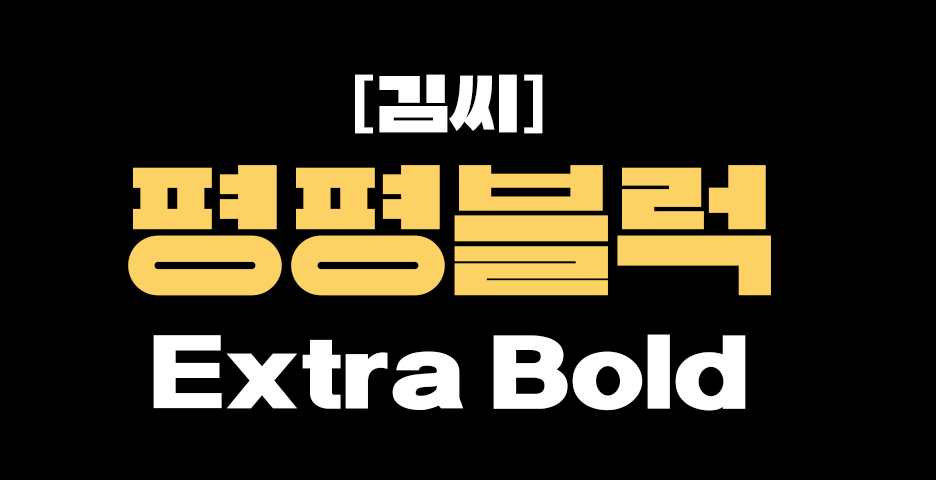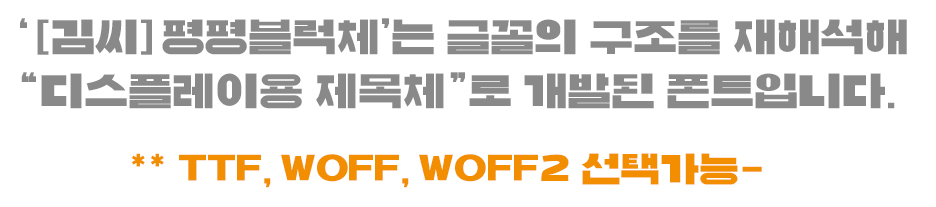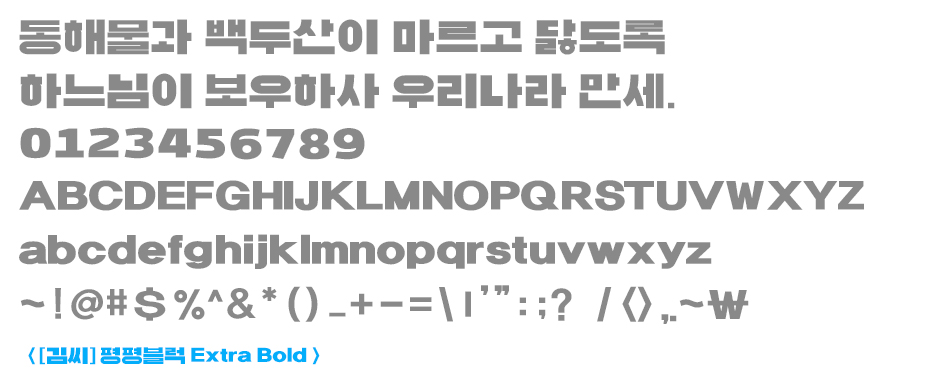
● ● 특장점
압도적인 실루엣과 초고중량(Extra Bold) 굵기
- 글자 내부의 속공간(음각 영역)을 줄이고, 획의 두께를 굵게하여 강렬한 시각적 인상과 높은 시선 집중도를 제공합니다.
넓은 평체(Flat) 비율과 꽉 찬 모듈
- 글자의 가로축을 넓히고 높이를 눌러둔 형태의 평체 비율을 적용해, 네모꼴 틀에 꽉 차는 단단하고 안정적인 블럭(Block) 형태의 조형미를 완성했습니다.
직선성과 기하학적 명확성
- 곡선 사용을 최소화하고 직각·직선 중심의 획 구성을 취해 현대적이면서도 위트 있고 팝(Pop)한 키치 감성을 전달합니다.
속공간의 슬릿(Slit)화 처리
- 자음과 모음 사이, 혹은 획 내부의 빈공간을 칼로 잘라낸 듯한 가느다란 틈새(Slit)로 처리하여, 자칫 둔해질 수 있는 초고중량 폰트에 명확한 형태 구분감을 부여했습니다.